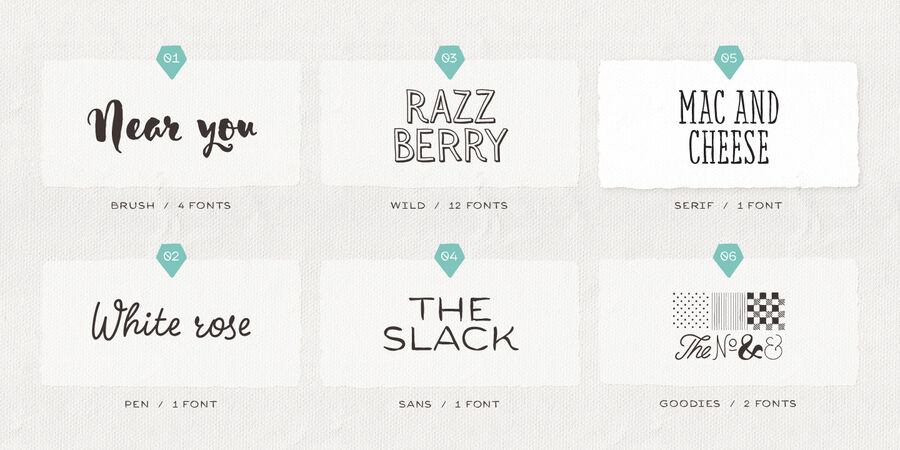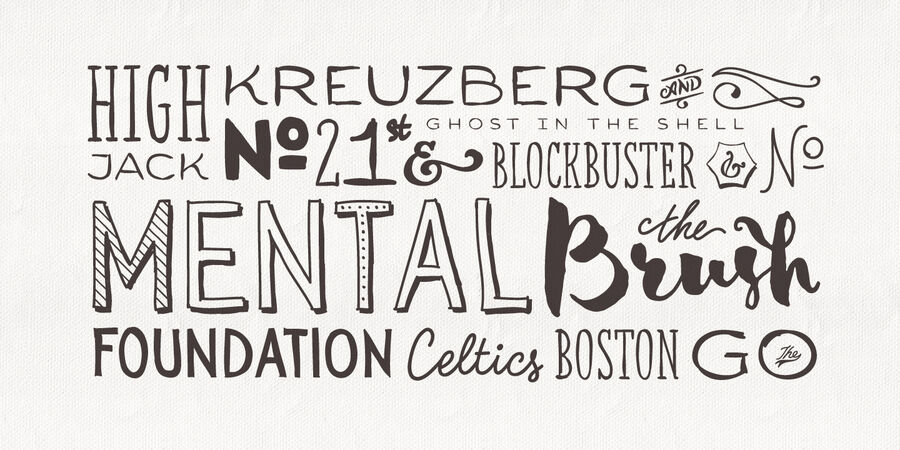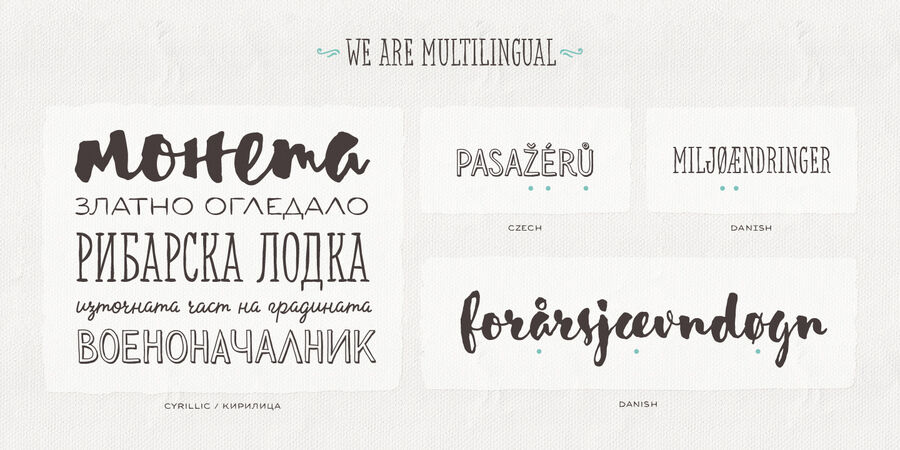
Шрифт Sensa – це сімейство шрифтів ручної роботи, що складається з 21 накреслення. Серед інших рукописних шрифтів цей поділяється на 6 підродин, кожна з яких вносить свій внесок у широкий діапазон настроїв – Sensa Brush, Sensa Pen, Sensa Wild, Sensa Sans, Sensa Serif та Sensa Goodies. Виберіть будь-який із шрифтів Sensa в якості провідного, а решта шрифтів можуть з легкістю супроводжувати його. Щоб працювати разом у всіх можливих комбінаціях, всі шрифти в цьому наборі створені з урахуванням цієї простої ідеї. Шрифт Sensa можна застосувати практично для будь-якого дизайнерського проекту – від реклами, упаковки, редакторських і брендингових робіт до веб, соцмереж та екранних проектів. Для краси та ніжних відчуттів або для більш чоловічого та сильного спілкування – у вас є широкий вибір. Гарнітура підтримує кирилицю. 2 шрифти Sensa доступні БЕЗКОШТОВНО. Функції OpenType: стилістичні альтернативи, контекстуальні альтернативи, розчерки, локалізовані форми. Шрифт розроблений командою Fontfabric в 2015-2018 роках.
хіпстерський, вуличний, вінтажний, побутовий, грубий, статичний, старомодний, ремісничий, працьовитий, надійний, консервативний, чесний, дерев'яний, рукотворний, ручний, ностальгічний, зрозумілий, доступний, зелений, натуральний, природний, теплий, ламповий, робочий, мотивуючий, крафтовий, органічний, пивний, артізанальний, домашній, довірчий, осінній, свіжий, екологічний, традиційний, зрілий, художній, іронічний, кустарний, саморобний, олдскульний, оригінальний, модний, живий, характерний, привітний, доброзичливий, приємний, симпатичний, потішний, легковажний, сміливий, неформальний, легкий, цікавий, мультяшний, худий, стрункий, високий, лісовий
торгівля, продукти, запас, склад, ящик, ремесло, коваль, м'ясо, тесля, деревина, хенд мейд, ярмарок, кафе, закуска, їжа, пиво, відпочинок, крамниця, фермер, природа, взуття, кава, обід, вечеря, гамбургер, Барбершоп, Інстаграм, дача, осінь, дитяча книжка, інтер'єр, анімація, чай, кухня, селфі, Хюґе, графіка, ілюстрація, дім, дієта, гра, зошит, канцтовари, щоденник, мультфільм Гарнітура має ознаки стилів: